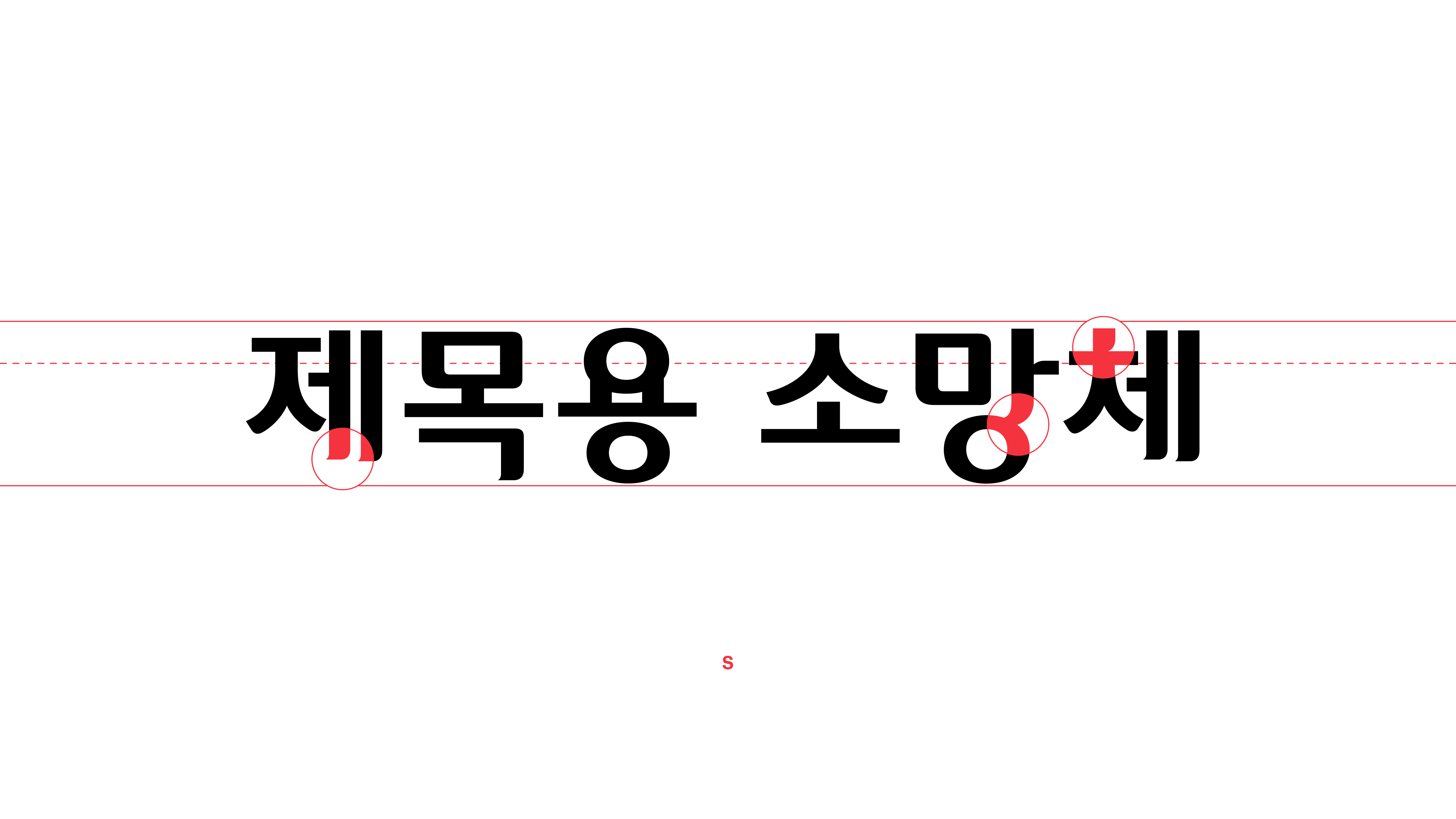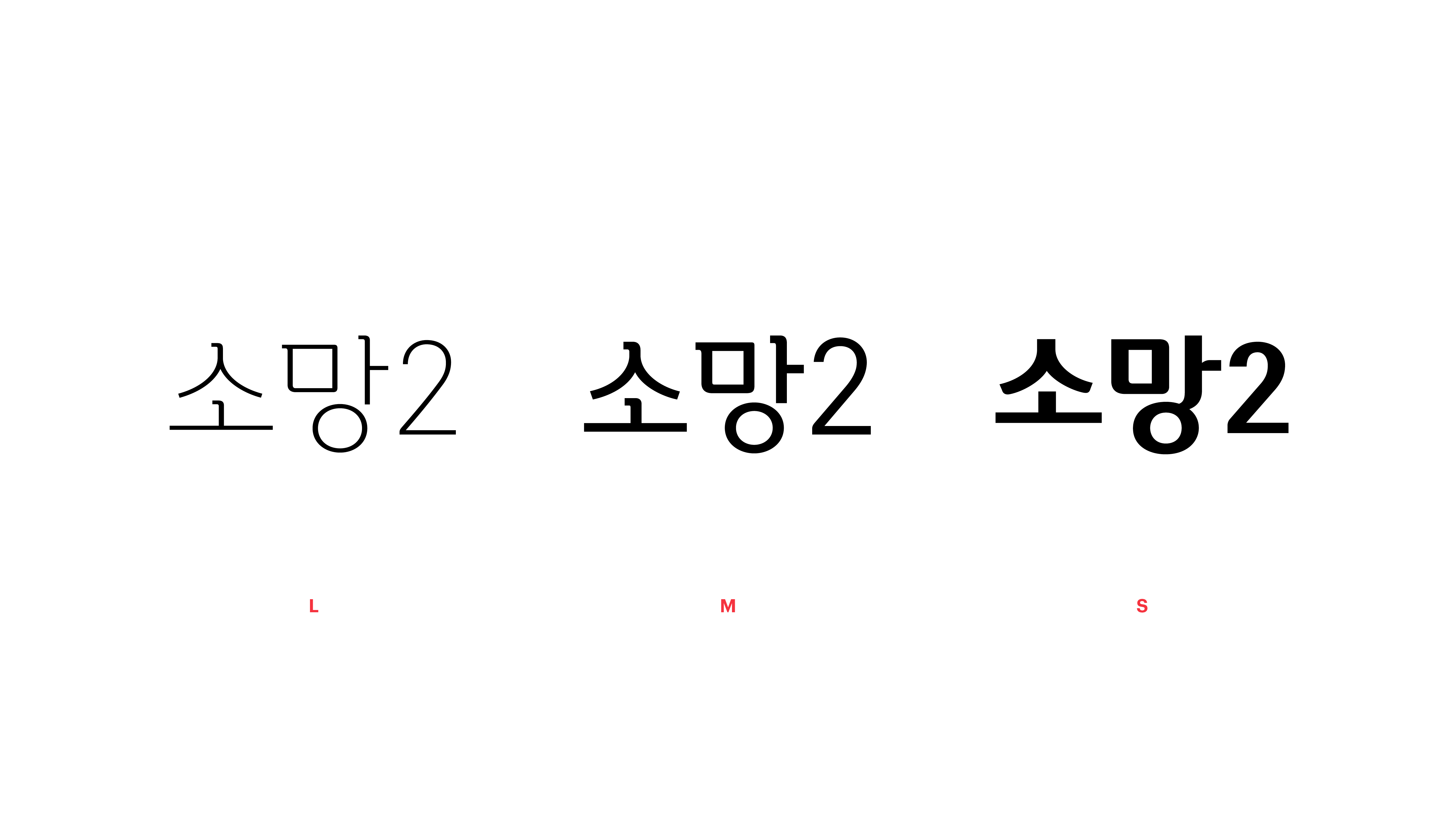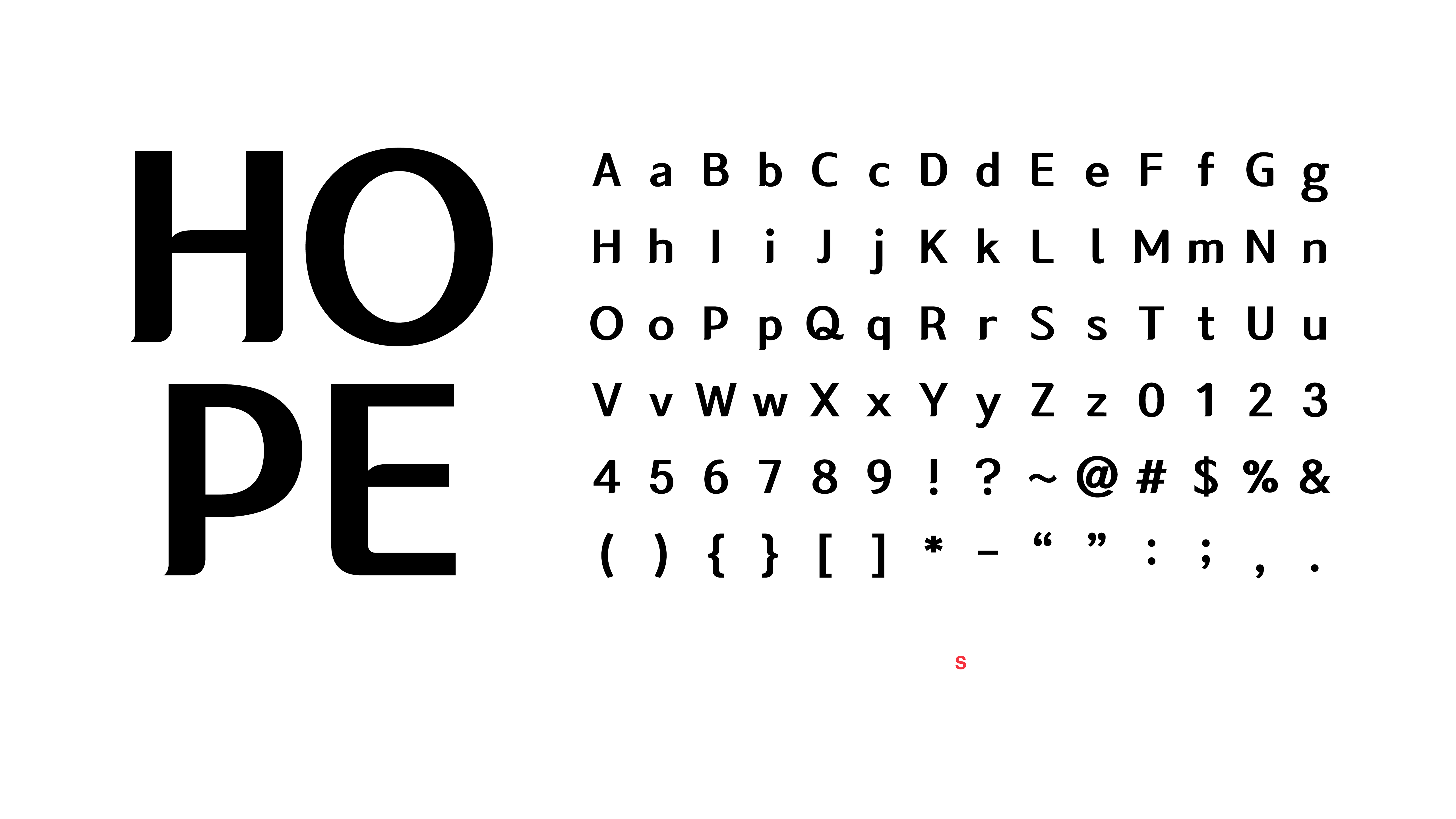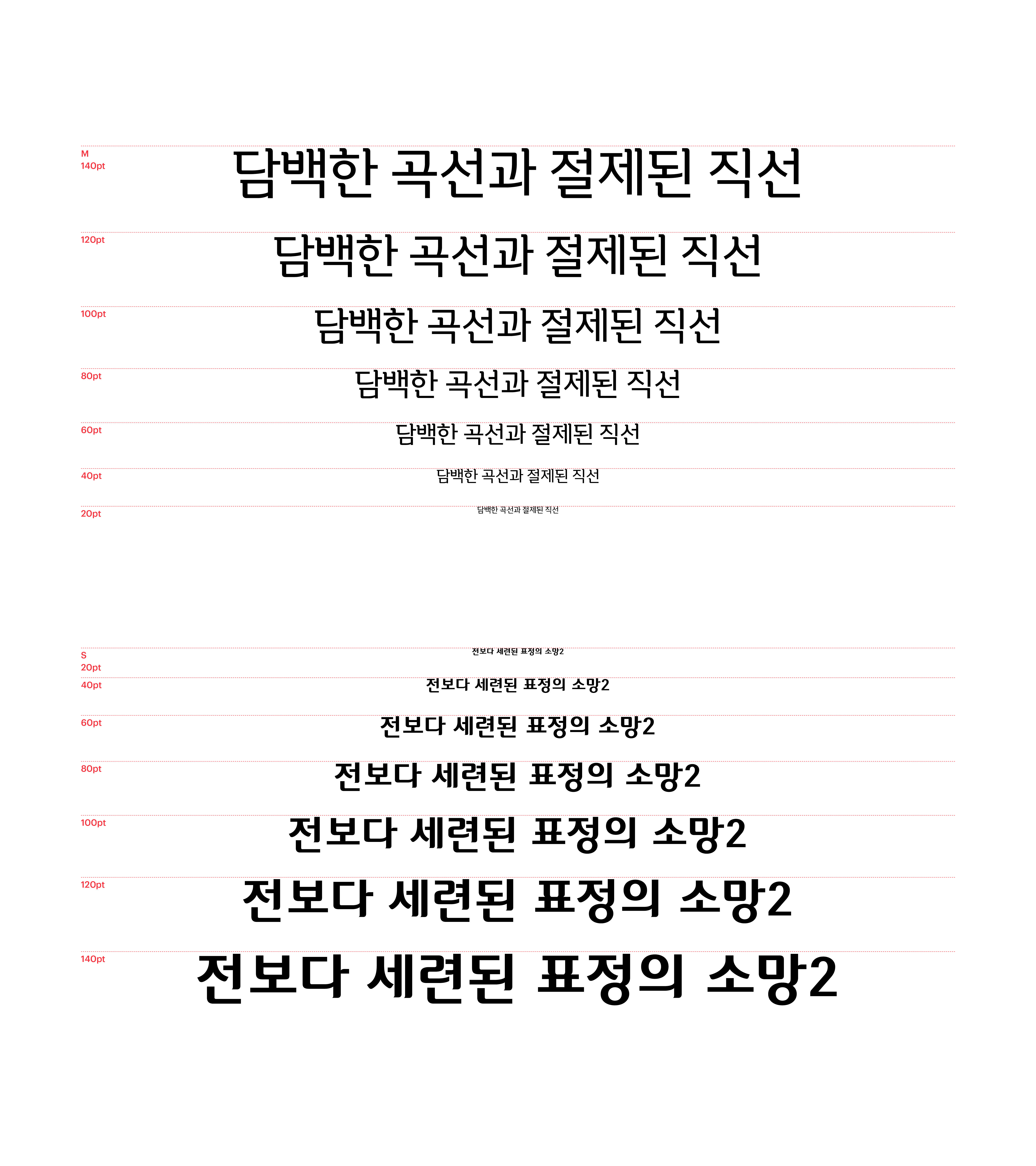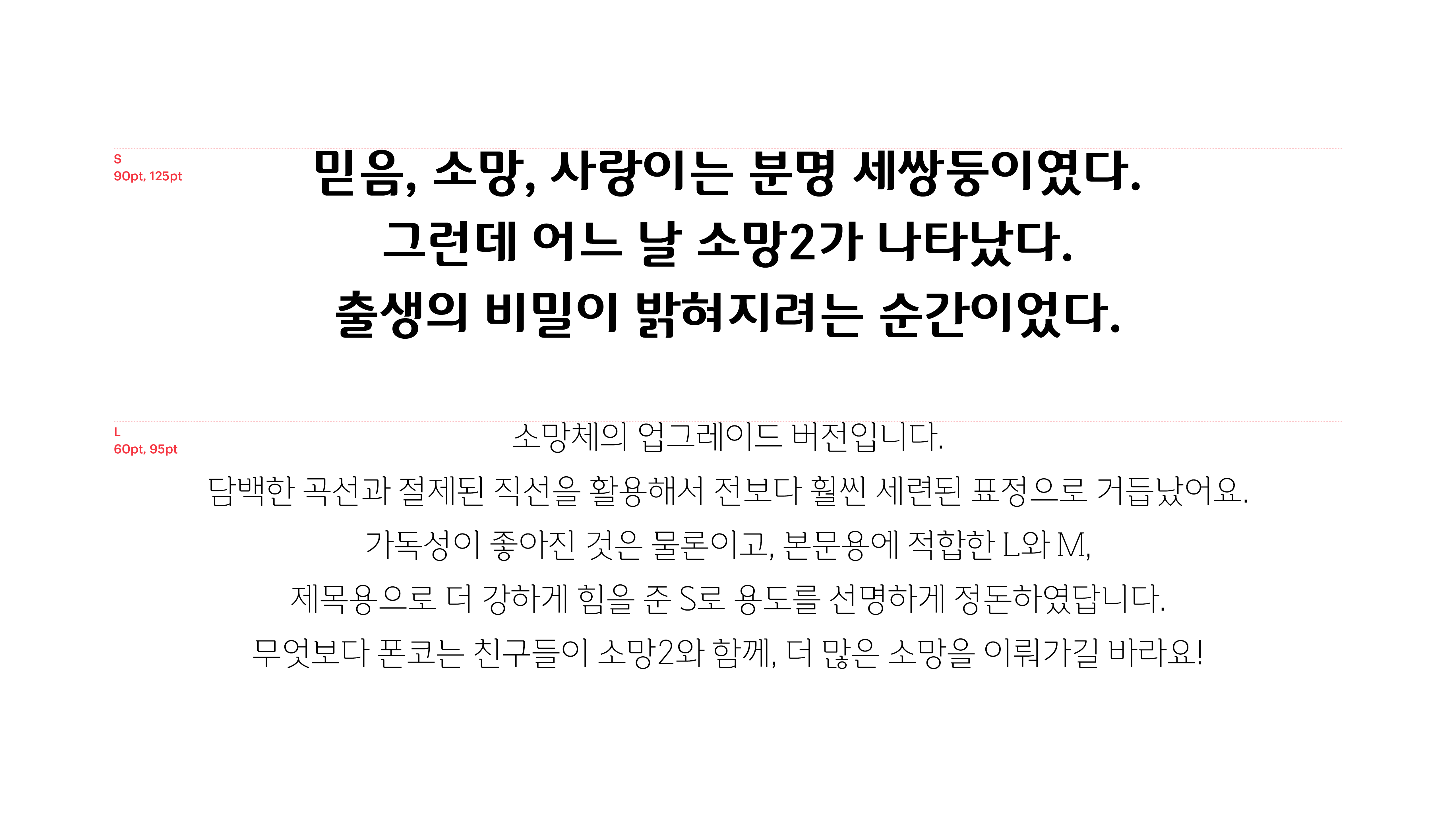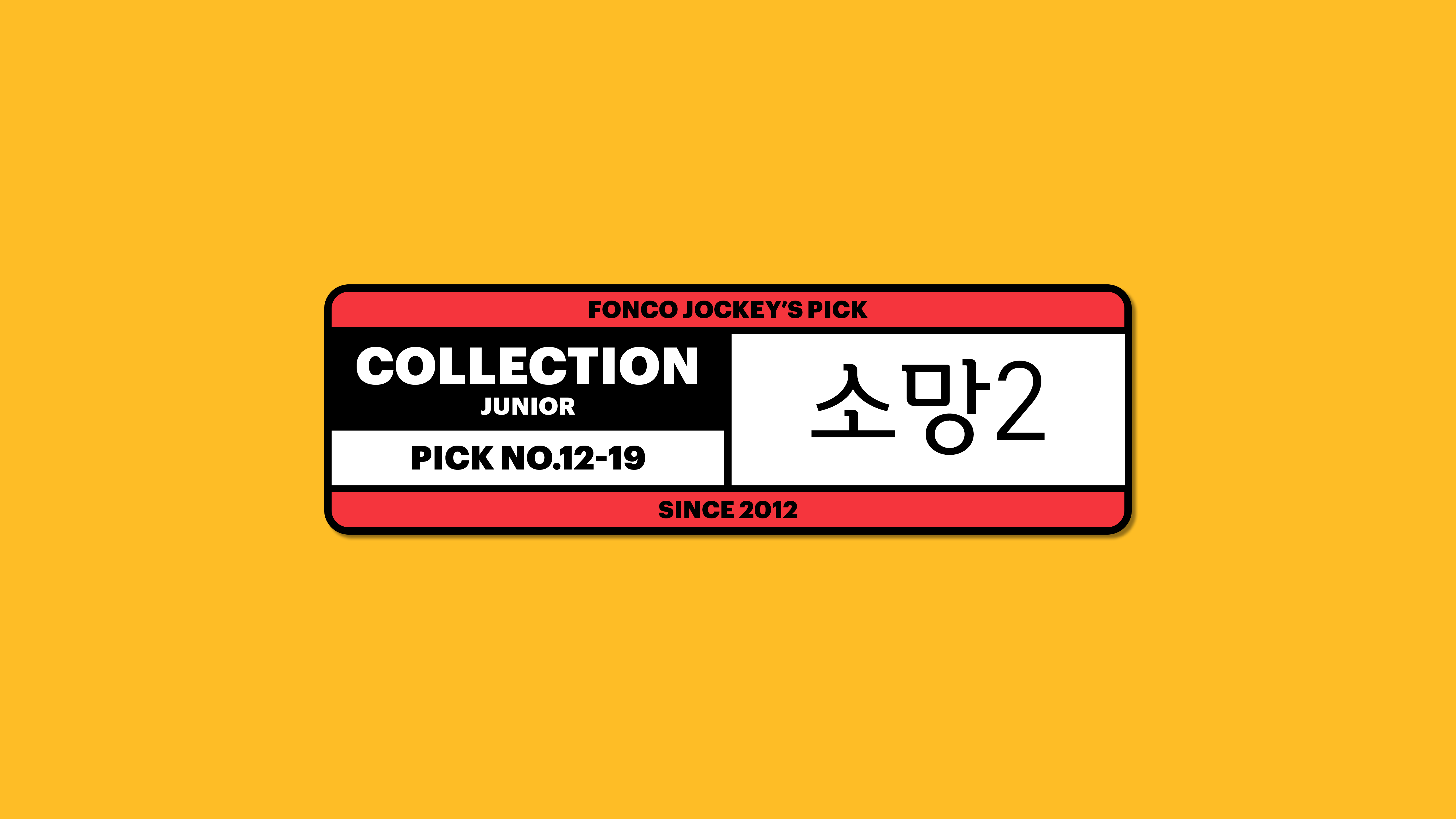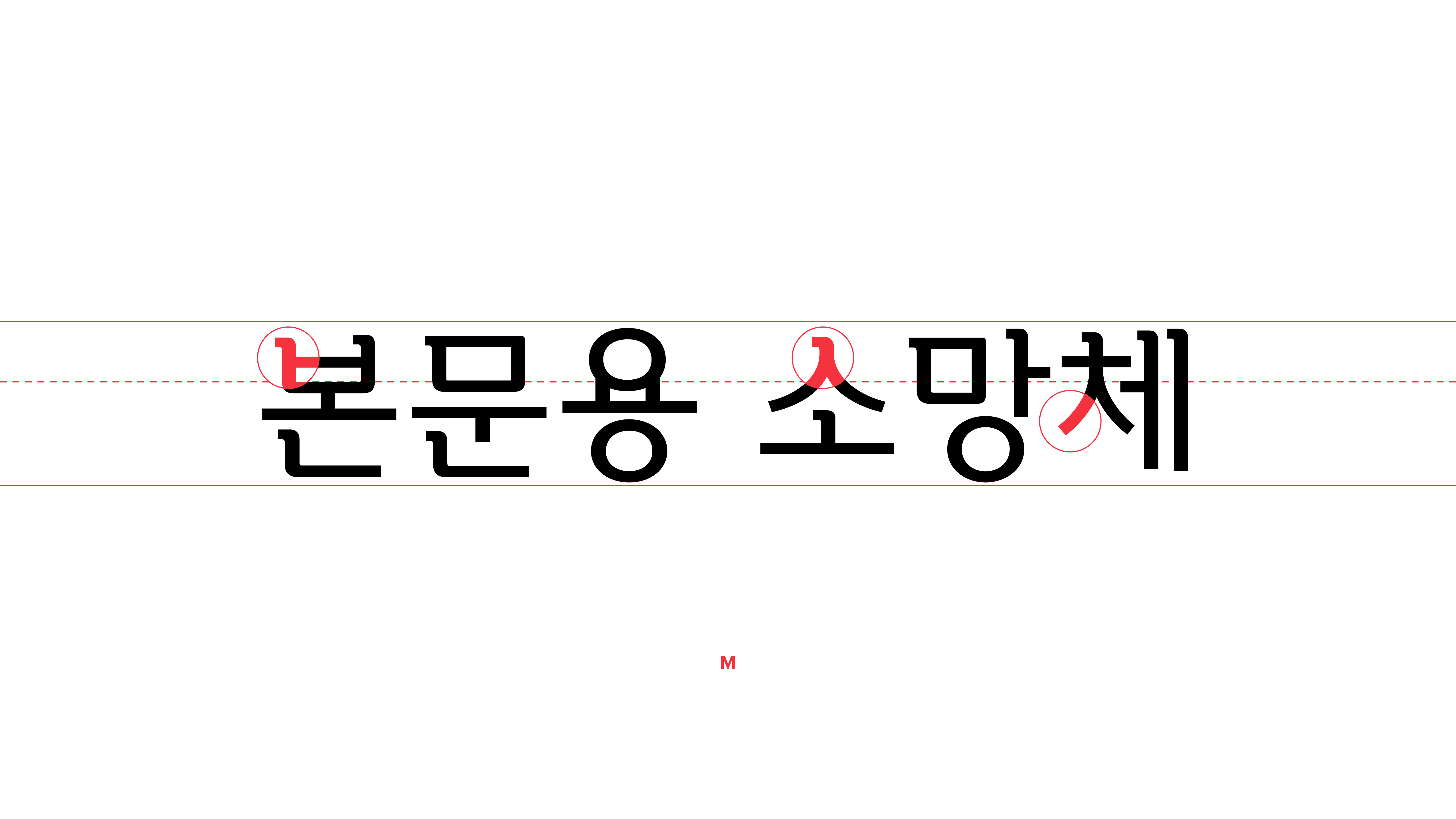
소망2
Yoon 소망2
소망체의 업그레이드 버전입니다. 담백한 곡선과 절제된 직선을 활용해서 전보다 훨씬 세련된 표정으로 거듭났어요. 가독성이 좋아진 것은 물론이고, 본문용에 적합한 L과 M, 제목용으로 더 강하게 힘을 준 S로 용도를 선명하게 정돈하였답니다. 무엇보다 폰코는 친구들이 소망2와 함께, 더 많은 소망을 이뤄가길 바라요!